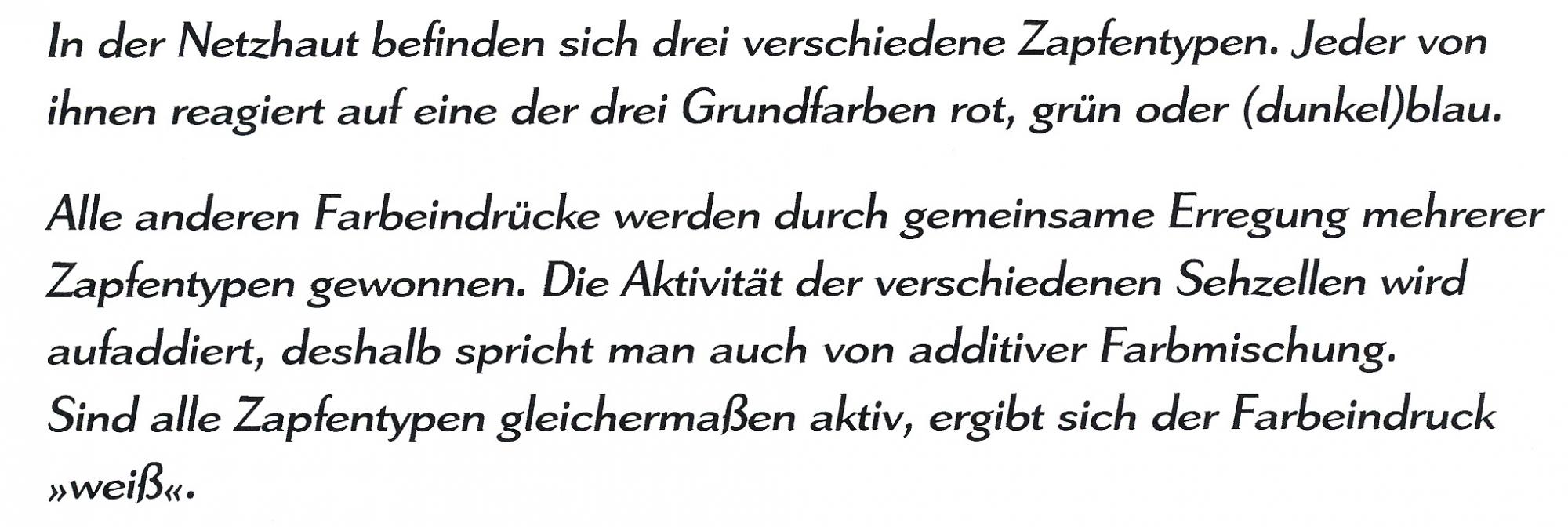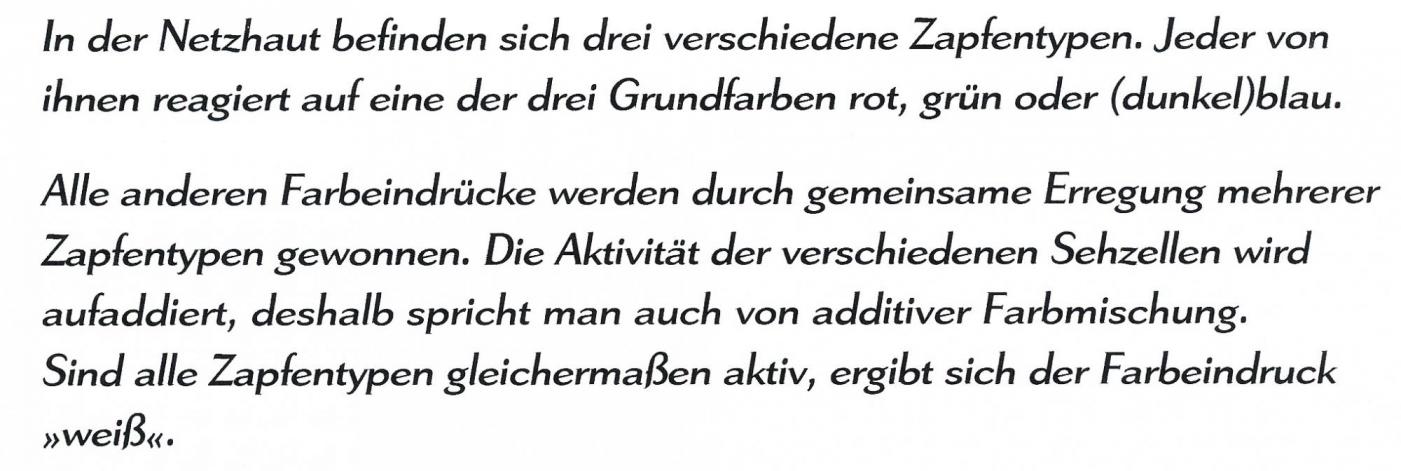
Schrift aus Mac OS von ca. 2002 gesucht
Ich habe zwischen 2002 und 2004 mit dem Programm ClarisWorks auf einem iMac viele Dokumente erstellt, in denen ich die gesuchte Schrift verwendet habe. Da das Programm auf neuen Macs nicht mehr lauffähig ist, versuche ich, die alten Dateien in .pdfs umzuwandeln. Leider besitze ich keinen Mac mehr, auf dem die fragliche Schrift installiert ist, so dass die Schrift beim Öffnen durch den Standard-Font Geneva ersetzt wird.
Die großen Oberlängen und das geschwungene z sind eigentlich ziemlich charakteristisch bzw. auffällig, aber ich bin bei meiner Recherche leider trotzdem nicht fündig geworden.
ich muss in den nächsten Wochen einen Uralt-Mac "untersuchen", da kann ich gern nachschauen, ob da noch vielleicht diese Schrift rumdümpelt...  Dauert halt noch n bissel, aber ich hab Dich im Hinterkopf.
Zeigt das Fontmenü oder irgendein Dialog denn nicht wenigstens die fehlende Schrift an? Oder wenn nicht im Originalprogramm, dann vielleicht in einem anderen Programm beim Import? Wenn du eine Beispieldatei zur Verfügung stellst, könnten wir das auch probieren.
vielen Dank für den Tipp, nochmals den Versuch zu unternehmen, die Dateien in ein anderes Programm zu importieren. Das Original-AppleWorks bzw. ClarisWorks ersetzt die Schrift kommentarlos und das aktuelle Pages kann .cwk-Dateien erst gar nicht öffnen. Aber ich hatte tatsächlich noch ein altes Pages 4.5, was die Dateien wenigstens öffnet und  Fehler wie fehlende Schriften anzeigt. Von alleine wäre ich nicht auf diese (eigentlich naheliegende) Idee gekommen...
Die fehlende Schrift heißt Bertrand (vermutlich stammte sie ursprünglich von einer frühen MacMagzin-CD aus den 1990er Jahren).
Im Internet habe ich dazu nichts gefunden; aber dann habe ich tatsächlich auf einer externen Festplatte eine wirklich uralte Datensicherung entdeckt, wo auch ein Ordner mit Fonts existiert, die ich früher mal benutzt oder wenigstens gesammelt habe. Wie gut, wenn man nichts wegwirft... 🙂